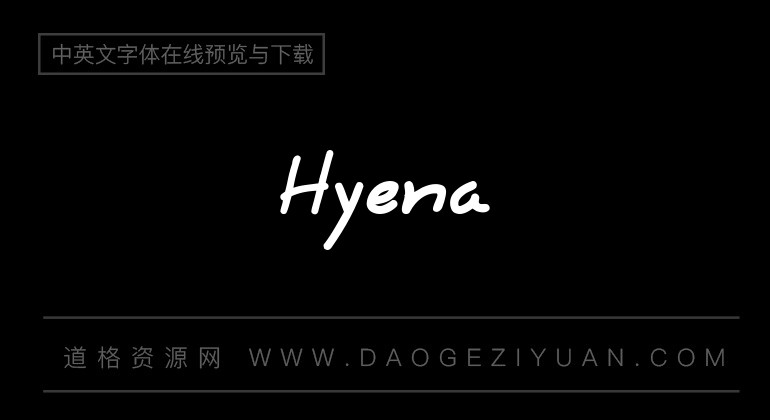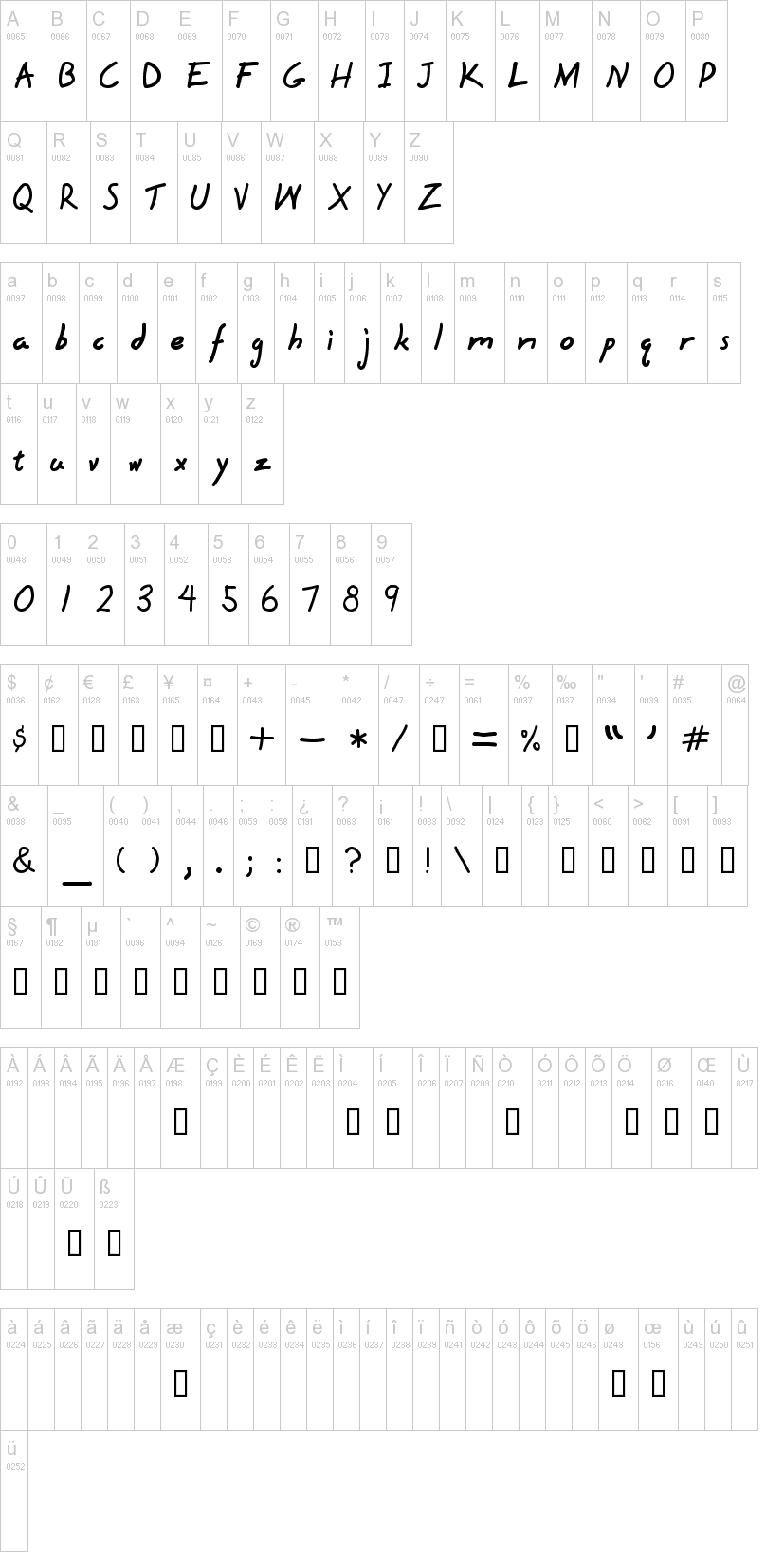
? Hyena 字体是一款免费的现代毛笔字体,由西班牙设计师 Mario Arturo 创作。它的特点是笔画粗细变化自然,拥有自然的折线,以及清晰的字形。Hyena 字体可以用于制作海报、标题、标签、网页和其他设计作品,为你的设计项目增添一份独特的魅力。内容介绍
Hyena是一款非常不错的手写艺术字体,具有很好的视觉感,适合于文化类的宣传设计、商业类品牌的广告和产品包装设计以及个性化文字排版等较多场景。